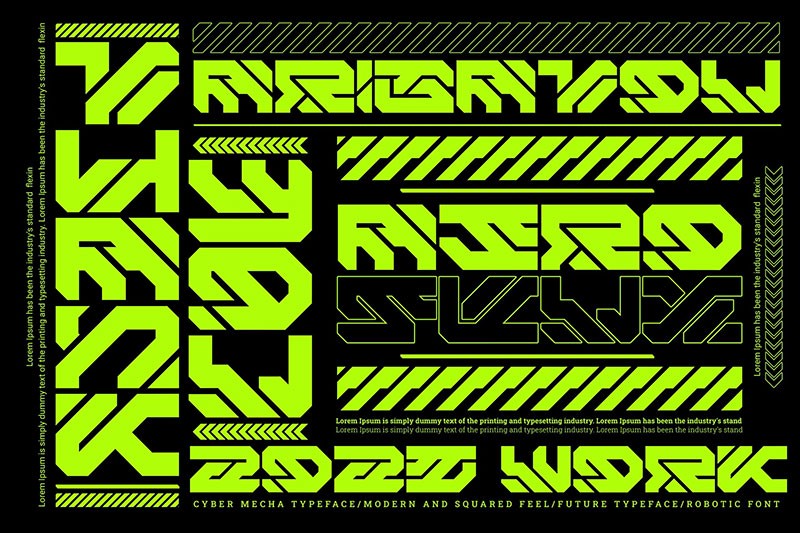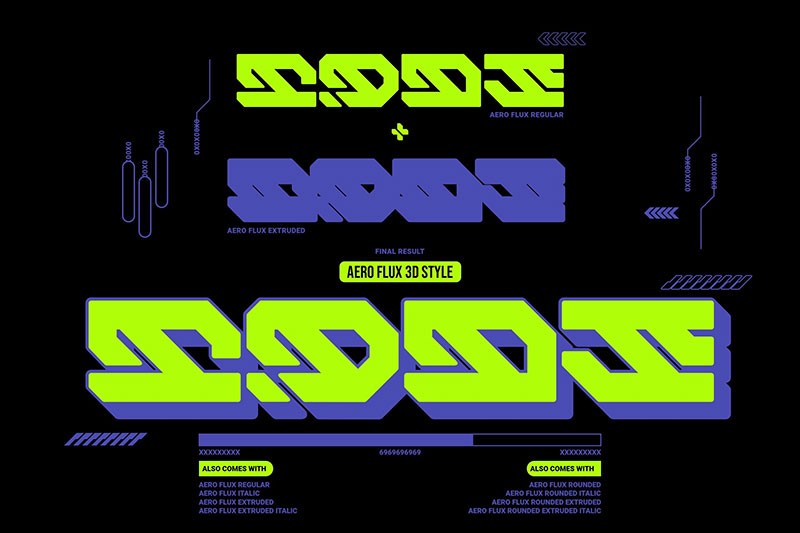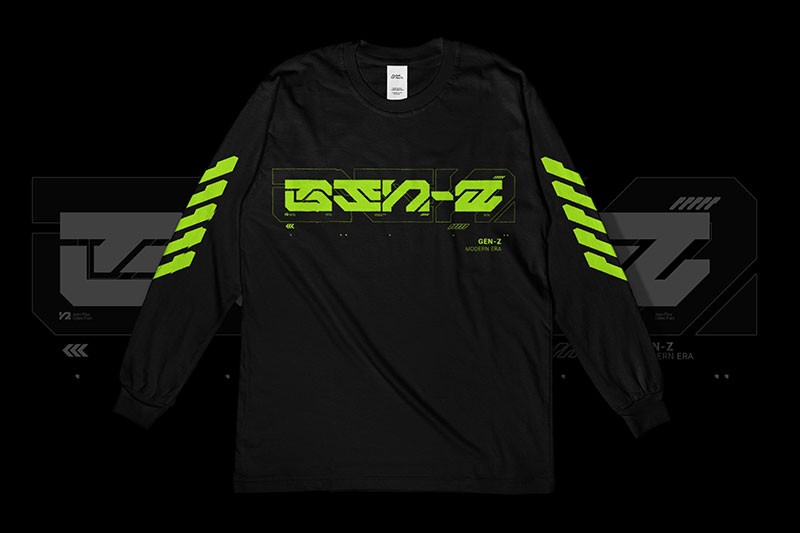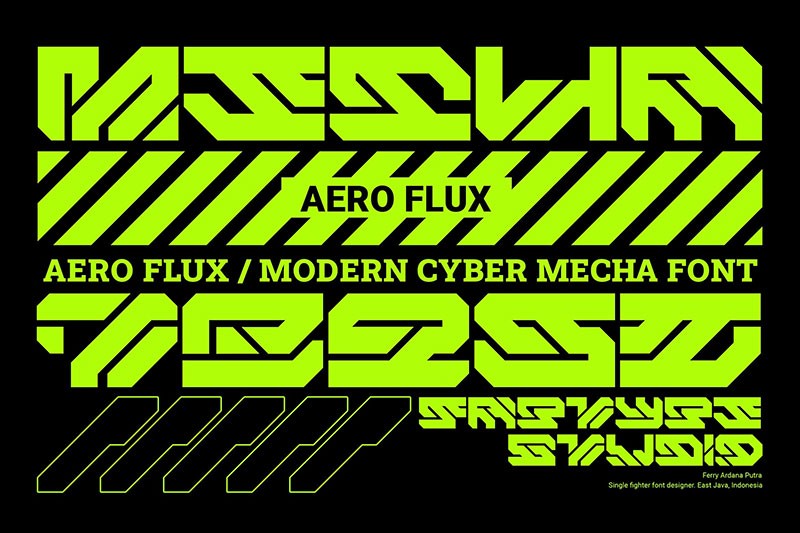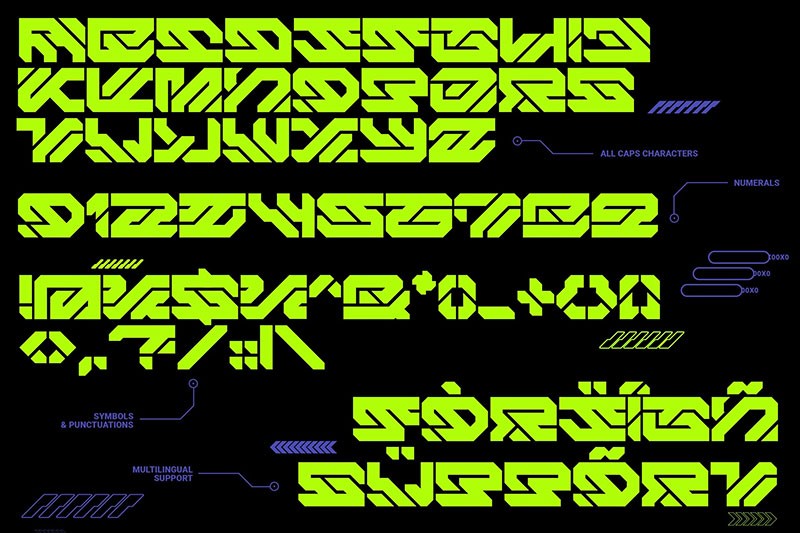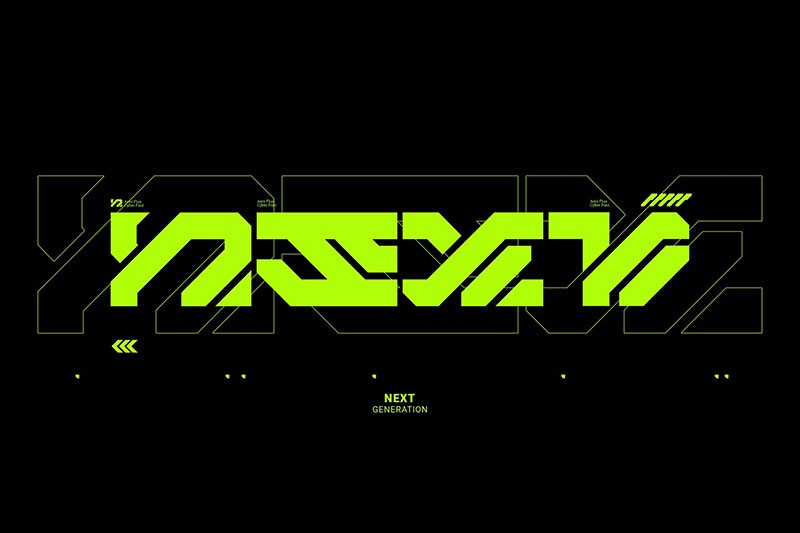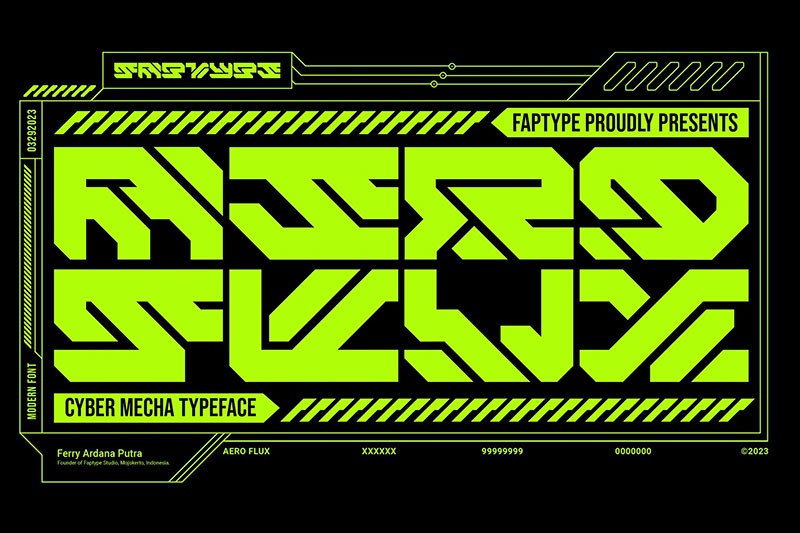
AeroFlux现代感机甲字体完整版
一款极具机甲风的现代英文字体,设计灵感源自现代航空技术和飞行器的动态外观。其流畅的曲线和精细的线条营造出强烈的动感和科技感。Aero Flux共有8种字重,包括超轻、细、黑体和粗体,以及斜体和粗斜体等多样化的风格,适用于品牌标志、海报、网站设计、广告和印刷品等。